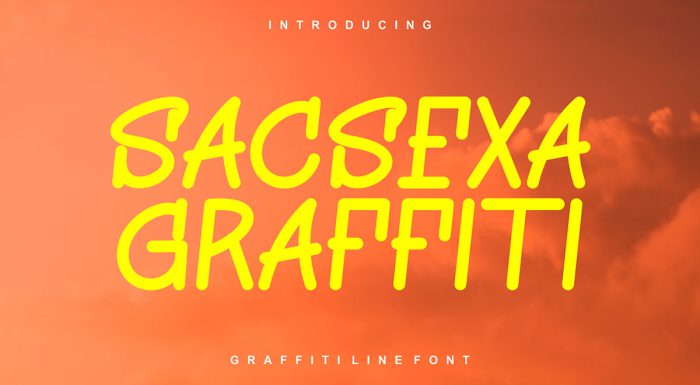
فونت Sacsaxa Graffiti انگلیسی
دانلود فونت Sacsaxa Graffiti انگلیسی Font ساکساکسا گرافیتی |
| ⭐ توضیحات | معرفی محصول جدید ** قلم SacsaxaGraffiti** – فونت مدرن
** فونت SacsaxaGraffiti ** – فونت مدرن یک فونت نمایشگر برجسته و معتبر است. این فونت برای هر پروژه برندسازی مانند لوگو، esport و بسیاری موارد دیگر مناسب است. برجسته در طیف گسترده ای از زمینه ها. |